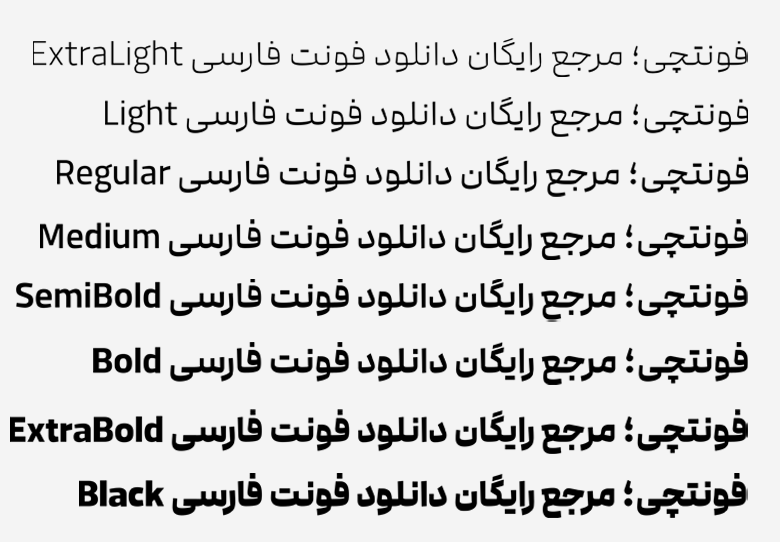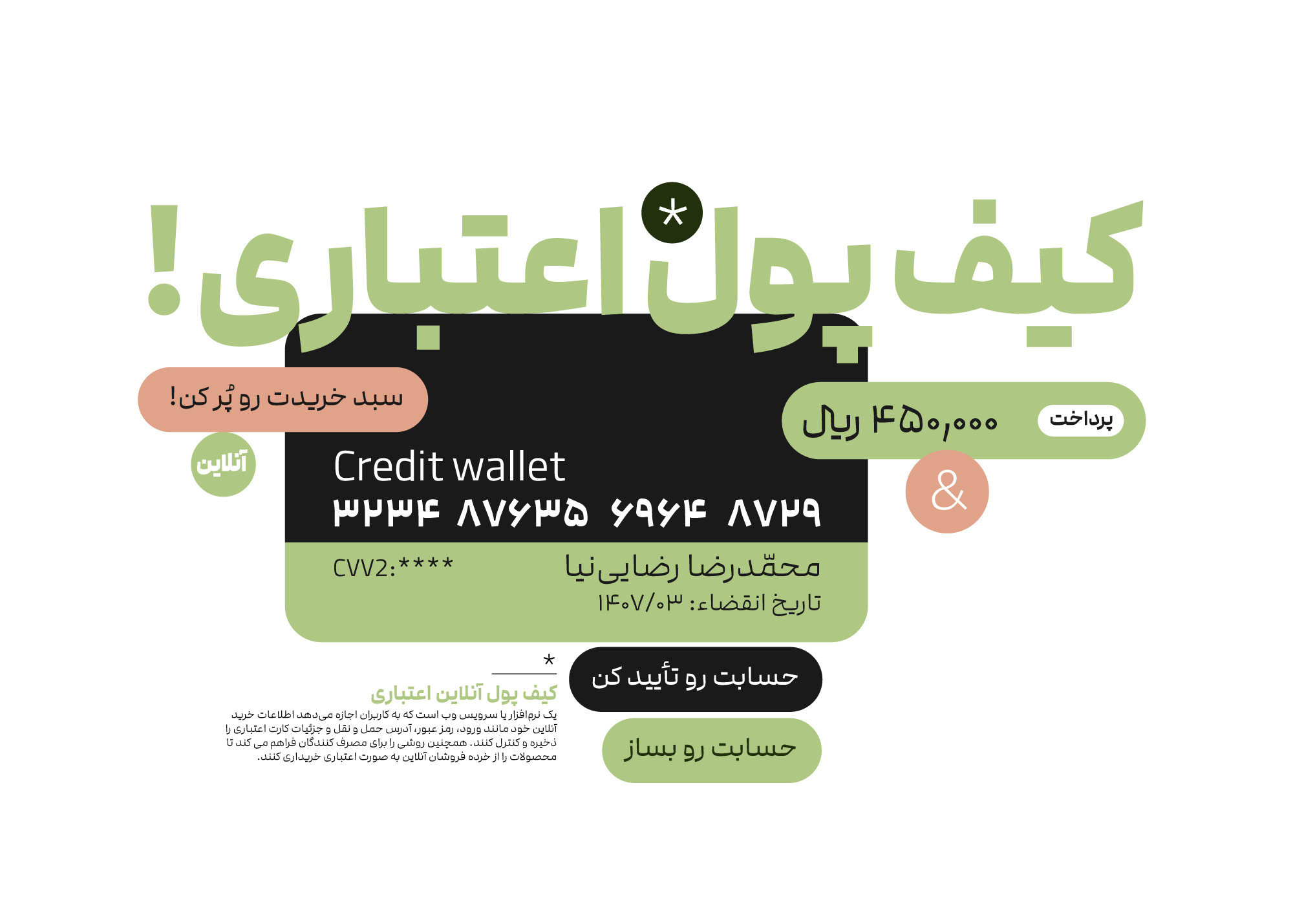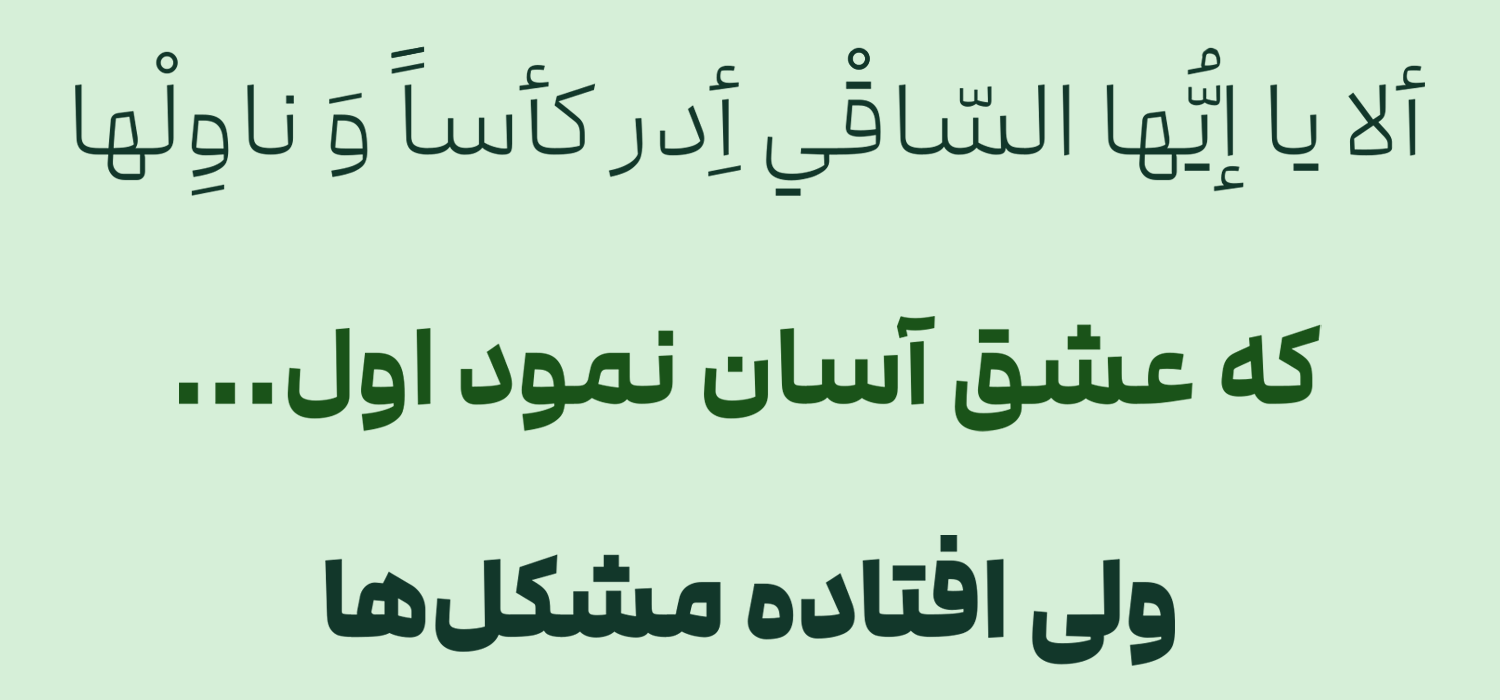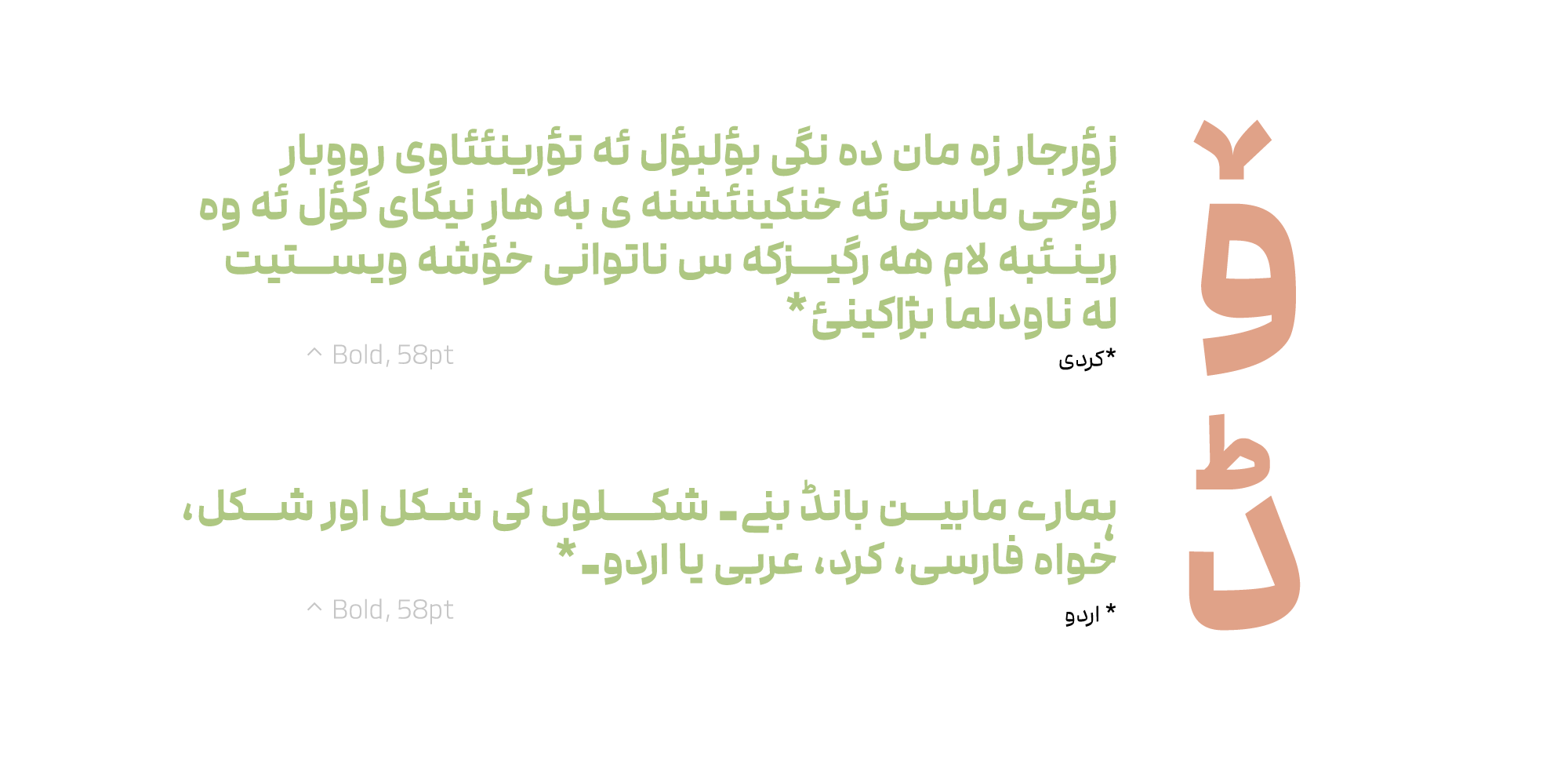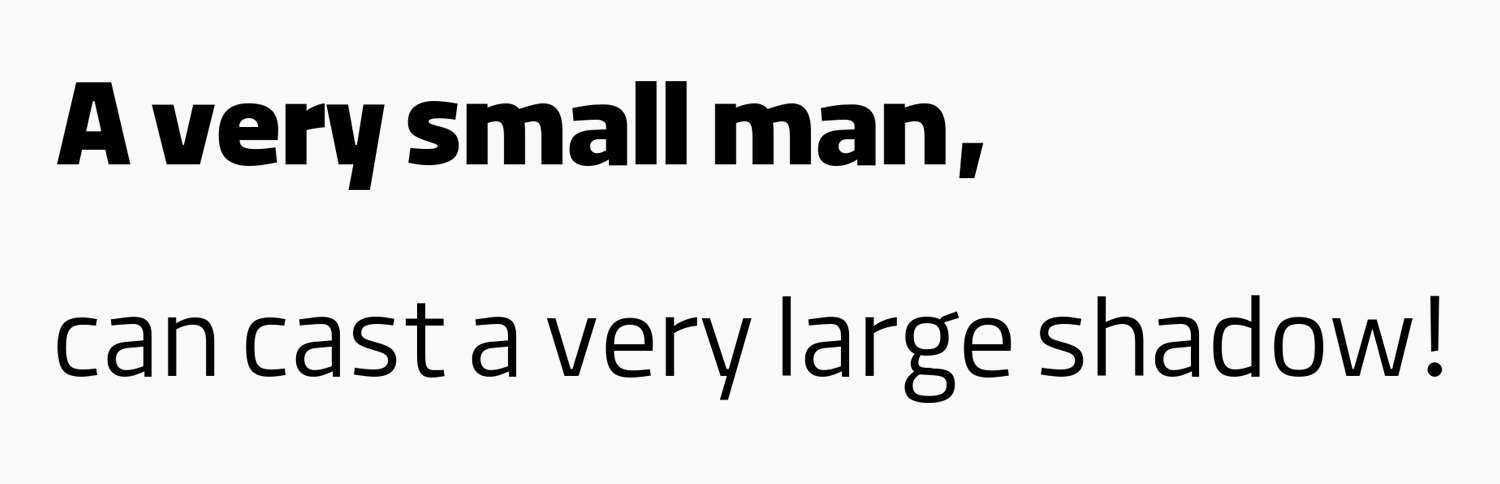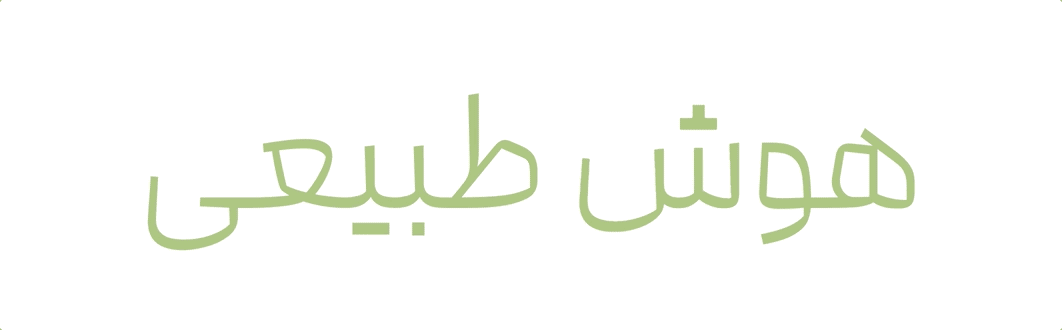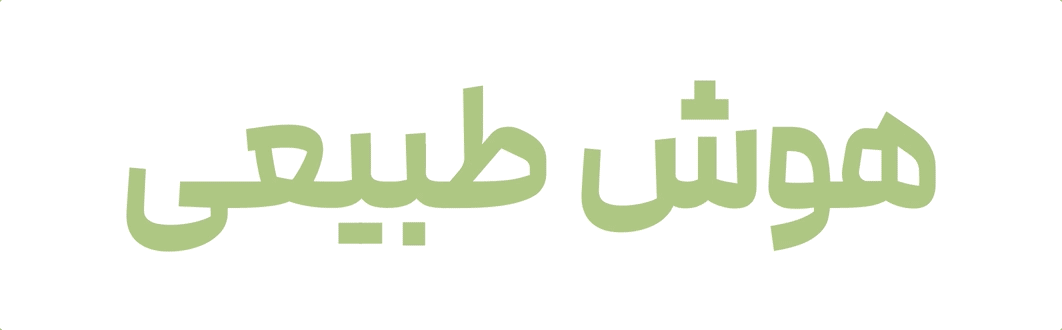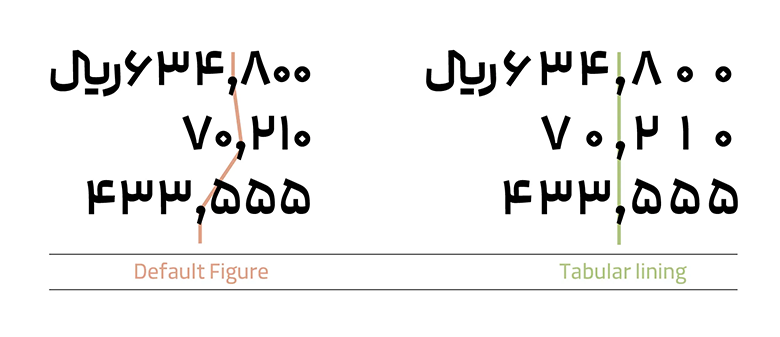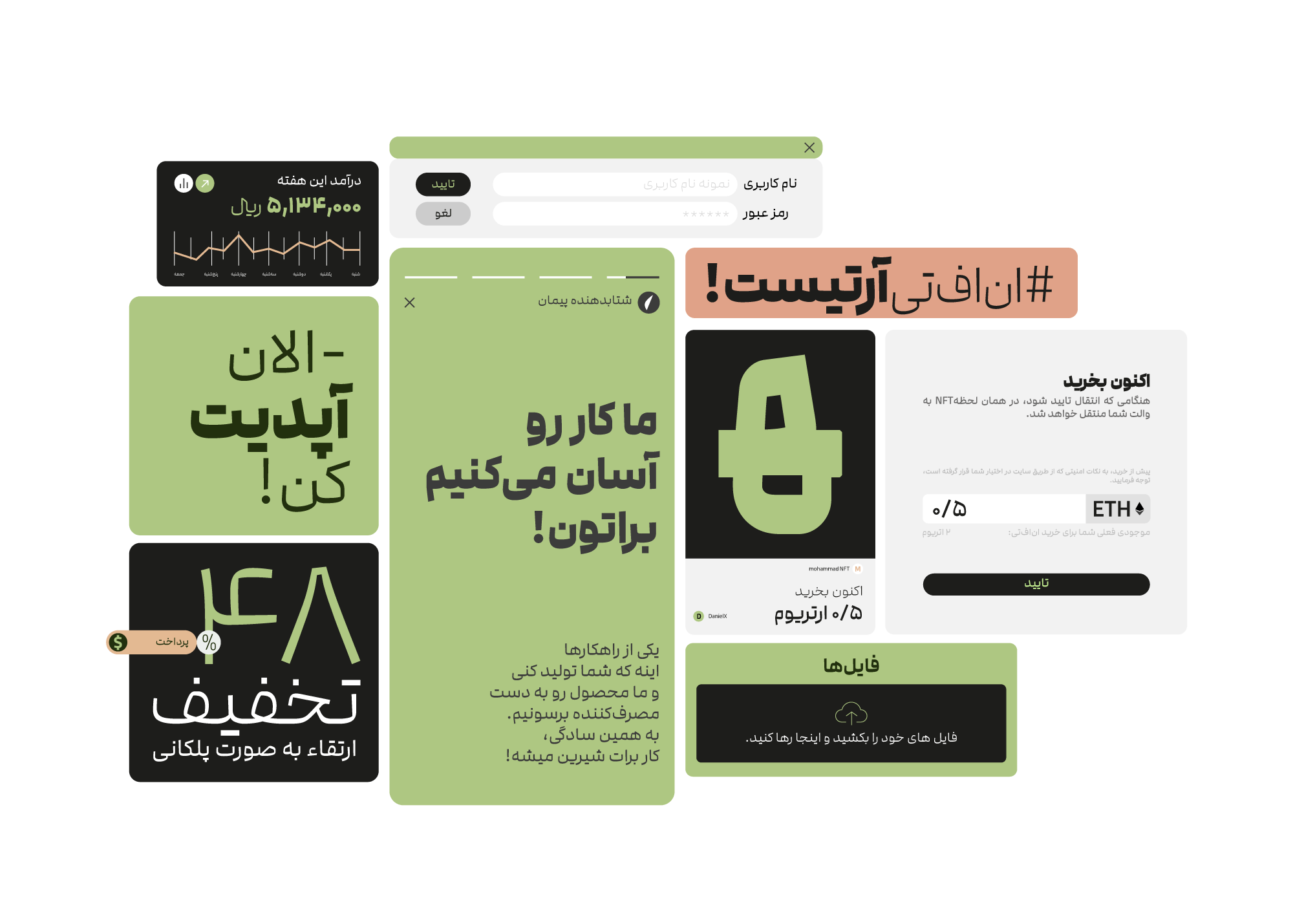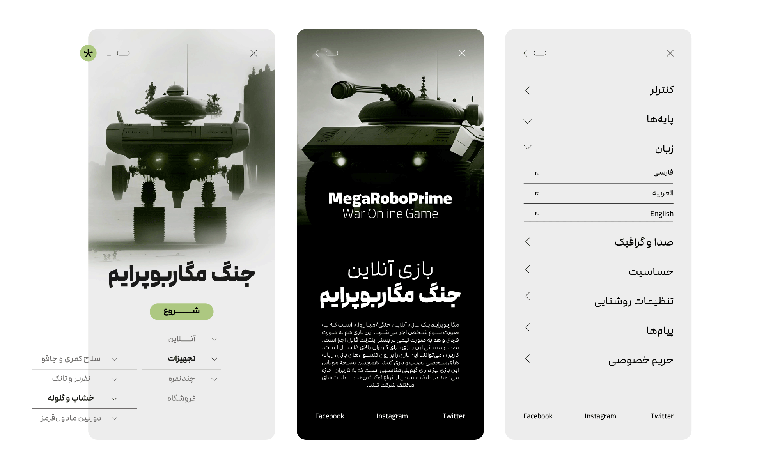
فونت مدام (Modam)
| طراح | سید ناصر خادم |
فونت مدام (به انگلیسی: Modam) دارای ظاهری استخوانی و ضخیم است که مناسب متن بوده و ساختار هندسی آن دارای فضاهای باز و منفی است که سعی شده تا جای ممکن ضخامت نسبتا یکسانی داشته باشد. فونت مدام رایگان نیست و با وزنهای متنوع و نسخه وریبل که دارد، در ۳ بسته مختلف قابل خریداری است.
این فونت توسط سید ناصر خادم طراحی شده است که در ۸ وزن و دارای نسخه وریبل (فونت متغیر) نیز میباشد. ظاهر پهن در کنار ساختار هندسیاش کنتراست بالایی به آن داده است که همین امر موجب شده یک انتخاب عالی برای متنهای کوتاه، تیترها، عناوین و بهطور کلی مواردی که نیاز به جلب توجه کاربر است باشد.
در ادامه این نوشته به نقد و بررسی فونت مدام در وبسایت فونتچی میپردازیم که از این قلم میتوانید برای کارهایی که نیاز به یک قلم مناسب عناوین، تبلیغات و همچنین فونتی با ساختار متفاوت برای متون بلند هستید استفاده نمایید.
معرفی و بررسی فونت مدام (Modam)
فونت مدام نمایشی و متاسب عنوان است؛ این فونت میتواند به خوبی با شکل هندسی خاص خود در شکستگیها و منحنیهایی که دارد توجه کاربران را بیشتر جلب خود کند. از همینرو توصیه میشود که از این فونت برای سرتیترها و عناوین مهم استفاده کنید.
تفاوتی ندارد که یک بیلبورد فیزیکی را در مرکز شهر اجاره کرده باشید یا اینکه بخواهید از این فونت در فضای وب و اپلیکیشن استفاده کنید؛ در هر حالتی شکل خاص این فونت توجه بیشتر کاربر را برای خواندن محتوا جلب خواهد کرد. خصوصا در نسخههای ضخیم و وریبل فونت که امکان استفاده از چند حالت در نقطهگذاری حروف وجود دارد.
یکی از دغدغههای من، طراحی تایپفیسهایی برای استفاده در فضای بازیهای دیجیتال و مدیومهایی در بستر وِب است. در پاییز ۱۴۰۰ که در کلاسهای آنلاینِ طراحی تایپِ استادم دامون خانجانزاده شرکت کردم، این فکر و دغدغهام را با ایشان در میان گذاشتم و ایشان بسیار استقبال کردند.
از میان مباحث گستردهی تئوری، تجزیه و تحلیلهای فرمی و بصری، تحلیل کانسپ، اتودهای فرمی و در نهایت اتودهای طراحی حروف، این تایپفیس ساخته شد که آن را «مُدام» نام نهادم. فرآیند مطالعات، تحقیق و طراحی این تایپفیس و آنچه در این مسیر از جناب ایشان آموختم را بهصورت مقالهای جداگانهای منتشر خواهم کرد.
برای فشردهسازی این فونت ضخیم، تلاش شده تا فرم حروف همچنان حفظ شود و این فشردهسازی در آنها اعوجاج ایجاد نکند. همچنین میزان فشردگی و ضخامت حروف تا حد امکان ثابت مانده است؛ یعنی مثلا ضخامت حروف در وزن «معمولی» با وزن «معمولی فشرده» یکسان است و فقط فرم حروف فشردهتر شده است.
سبک طراحی و وزن فونت مدام
فونت Modam فارسی دارای ۸ وزن است که شامل نسخه «خیلی نازک، نازک، معمولی، متوسط، نیمه ضخیم، بولد، خیلی ضخیم و سیاه» است که در کنار این وزنها از نسخه وریبل متغیر نیز پشتیبانی میکند. تمامی وزنهای ارائه شده در این قلم بر پایه حروف هندسی طراحی شده که تا حدودی به خط نسخ نزدیک است.
ظاهر حروف در این قلم به صورت عمودی است و در حروفی مانند «م» پایانی که دارای کشیدگی قائم است، فاصلهای بعد از چشمی درنظر گرفته نشده و خط قائم به محض اتمام چشمی ایجاد شده است. ساختار فونت مدام رایگان همچنین فشرده است که برای استفاده در کارهای گرافیکی میتواند انتخاب خوبی باشد.
پشتیبانی از ۵ زبان متنوع
فونت فارسی مدام محدود به این زبان نبوده و از چندین زبان خاورمیانهای و لاتین پشتیبانی میکند. زبانهای عربی، اردو و کردی که بر اساس رسمخط فارسی هستند نیز توسط این قلم پشتیبانی میشوند. با این تفاوت که حروف متفاوت در این زبانها که متفاوت از نسخه فارسی هستند، گلیف اختصاصی خود را دارند.
بهعنوان نمونه «ك، ي، ة، ؤ، ئ» عربی یا «ﮧ، ﮩ، ے» اردو دارای گلیف خاص خود هستند که در صورت قرار دادن زبان سیستم عامل تایپ خواهند شد. در صورت نیاز میتوانید با دانلود فونت مدام برای فتوشاپ نیز از طریق تنظیمات اپنتایپ به تمامی گلیفها دسترسی داشته باشید و بدون نیاز به نصب زبان دیگر در سیستمعامل از طریق گلیف تایپ کنید.
فونت مدام رایگان همچنین از اعراب و کاراکترهای تزئینی که در زبانهای عربی، کردی و اردو وجود دارد پشتیبانی میکند. این نوع کاراکترهای با همنشینی درستی بر روی حروف قرار میگیرند تا در صورت استفاده همزمان چند کاراکتر روی یک حرف، موجب بههمریختگی کلیمه یا چسبیدن به حروف قبل یا بعد نشوند که در تصویر بالا نمونه آن را میبینید.
فونت modam انگلیسی دارای همان سبک طراحی فارسی است. بهطوری که حروف انگلیسی ضمن اینکه دارای یک زاویه خاصی در منحنیها هستند، تا حدی شکسته طراحی شدهاند که ظاهری دوستانه به خود گرفته است. شکل خاص گردی حروف انگلیسی و شکستگیهایی که فاقد برخی پیکسلهای حروف هستند، ظاهر این فونت را برای توجه و خوانایی بهبود داده است.
پشتیبانی فونت مدام وریبل
ویژگی دیگر فونت مدام پشتیبانی از نسخه وریبل است که به شما این امکان را میدهد بدون نیاز به استفاده از ۸ وزن مختلف این قلم در قالب فایلهای جداگانه، صرفا با نصب یک فایل فونت به تمامی این وزنها دسترسی داشته باشید که حجم آن هم کمتر از دو وزن خواهد بود.
نسخه وریبل فونت مدام صرفا قابلیت تغییر وزن را ندارد؛ بلکه از قابلیت تغییر عرض (فشردگی فونت) نیز پشتیبانی میکند. در بسته فونت متغیر ۱۶ وزن (۸ وزن + استایلهای فشرده) در قالب یک فایل فونت قابل استفاده است. این نسخه حجم بسیار کمی دارد و برای استفاده در وب انتخابی عالی از نظر بهینهسازی سایت است. چرا که به دلیل کاهش تعداد درخواست کمتر برای لود فونت در وزنهای مختلف به بهینهتر کردن صفحات وب کمک میکند.